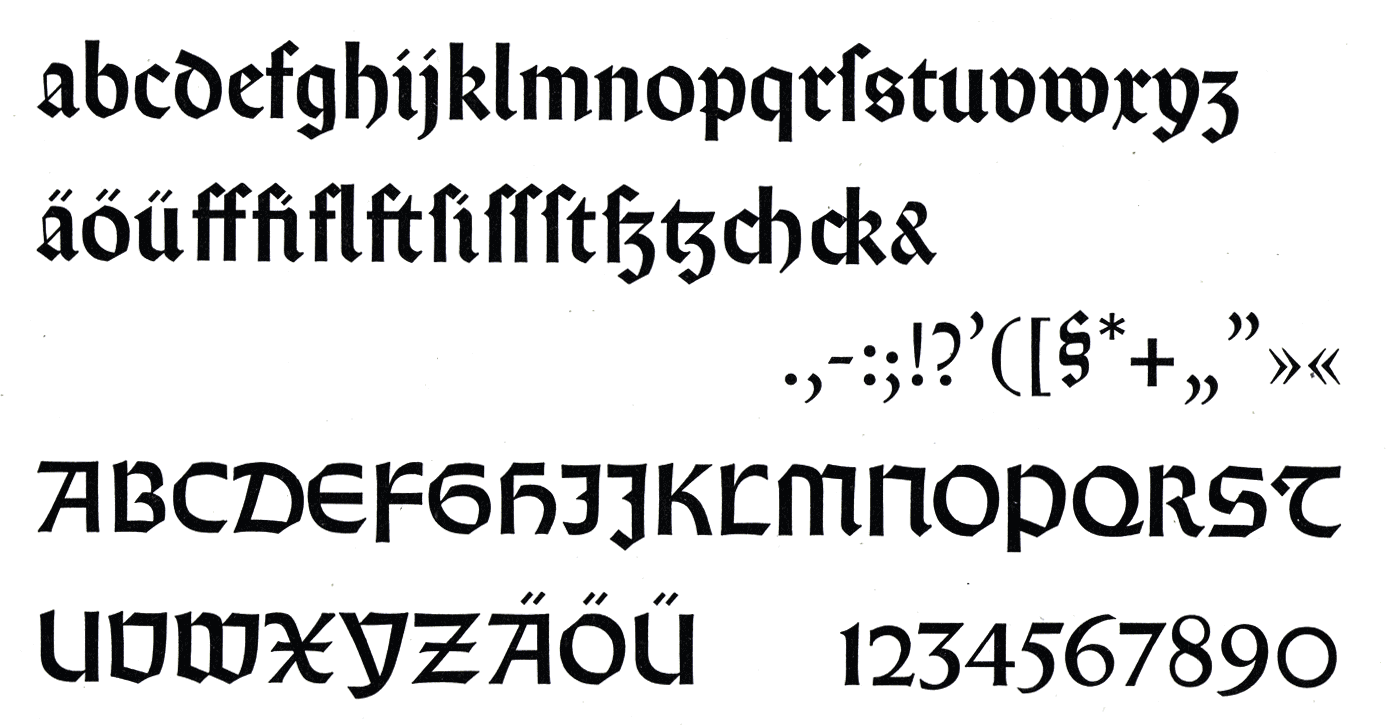
- 1937
- Gebrochene Schrift
Die Grundlage für die Rundgotisch von Emil Rudolf Weiß bildeten Alphabete des Augsberger Druckers Erhard Ratdolt. Dieser hatte eine Zeit lang in Venedig gearbeitet und war dort mit den für den südeuropäischen Raum typischen rundgotischen Schriften in Berührung gekommen.
Erste Entwürfe zur Schrift entstanden bereits 1915, doch sie erschien erst in den 1930er-Jahren. Digitalisierungen sind heute über URW++, Elsner+Flake sowie Linotype erhältlich. Linotype bietet neben der Standard-Version auch eine Com-Version mit 388 Glyphen. URW++ bietet einen zusätzlichen Antique-Schnitt mit rauer Umrisslinie.